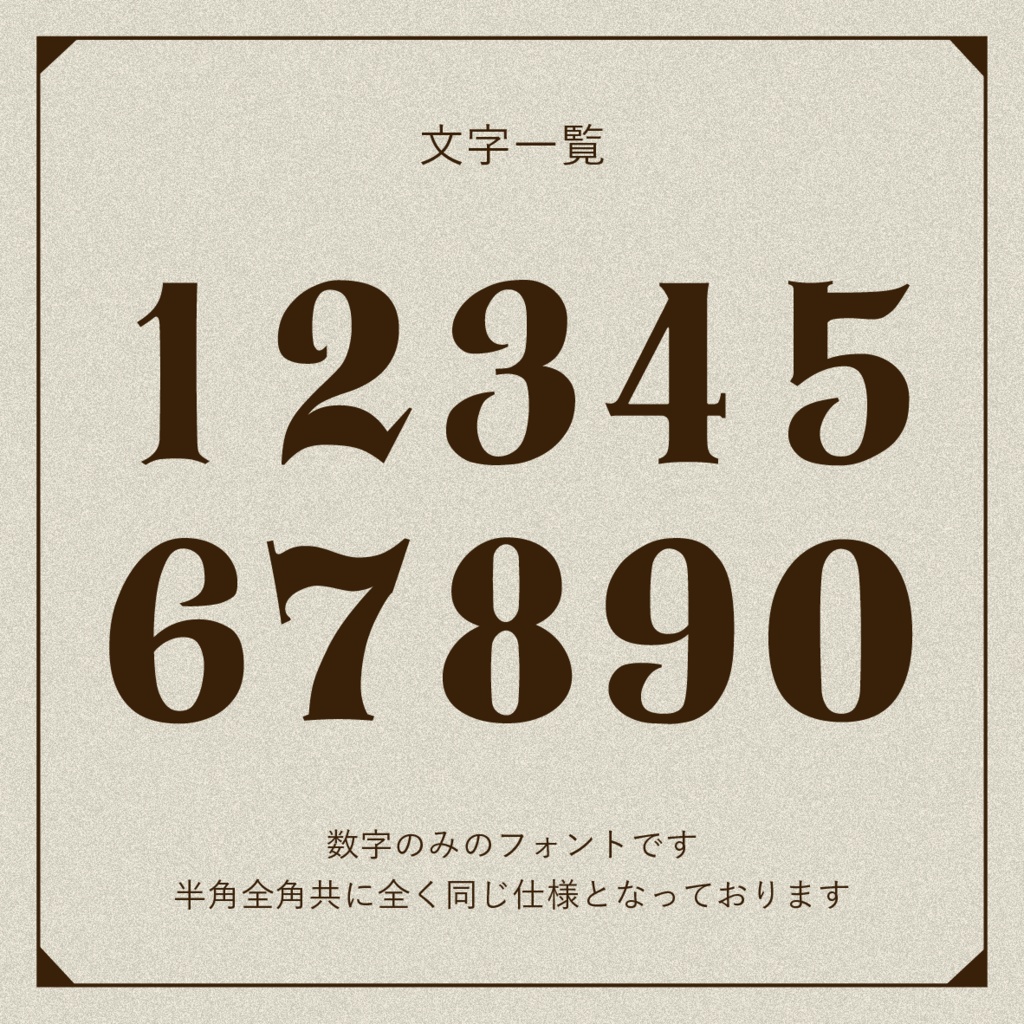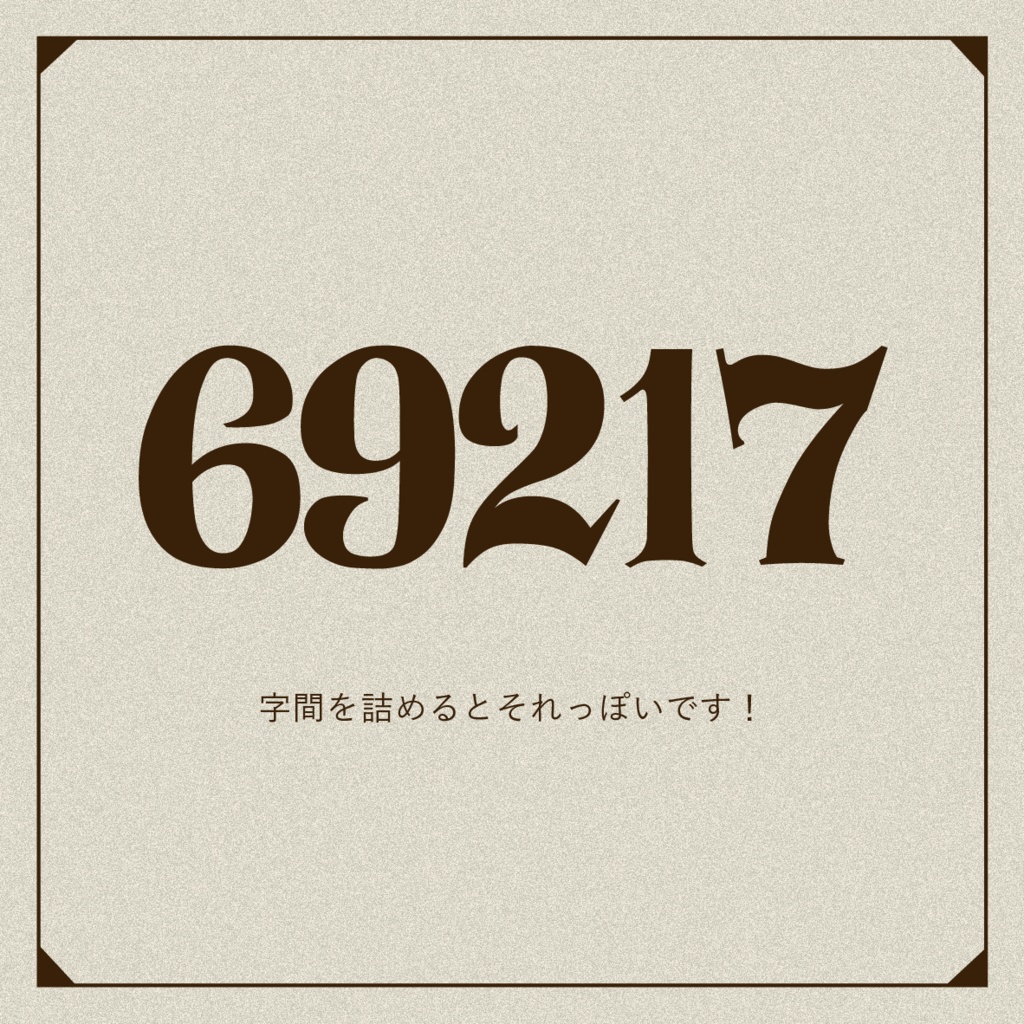
GFnumフォント
GFnumフォント(GFナンバーフォント)は約束のネバーランドの首筋認識番号を参考に制作されたフリーフォントです。 ●収録文字 数字0〜9のみ。半角全角どちらも同じように入力されます。 ●注意点 トレスではないので微妙なニュアンスは異なります。 フォント制作初心者が制作しておりますので何かしら不具合等あるかもしれません。ご理解のほどよろしくお願いいたします。 何か問題点がございましたらBOOTHやpixivのメッセージまでご連絡をお願いいたします。 ●利用規約 ・当フォントは原則個人利用でのみご利用いただけます。ただし、利益を目的としない同人誌等での利用につきましては可能です。 ・商標を取得するロゴ等へのご使用はご遠慮ください。 ・フォントデータの再配布、複製、改変したデータの頒布や販売等は禁止です。 ・自作発言等は禁止です。 ・OSやソフトウェアによってはフォントを読み取れない場合もございます。 ・Windowsでの動作確認は行なっておりません。 ・フォントのインストールや使用による不具合・損害に関しては一切の責任を負いません。ご自身の責任でご使用ください。 ●更新情報 2025/08/23 フォント名をGFnumフォントに変更しました。フォント自体に変更はございません。